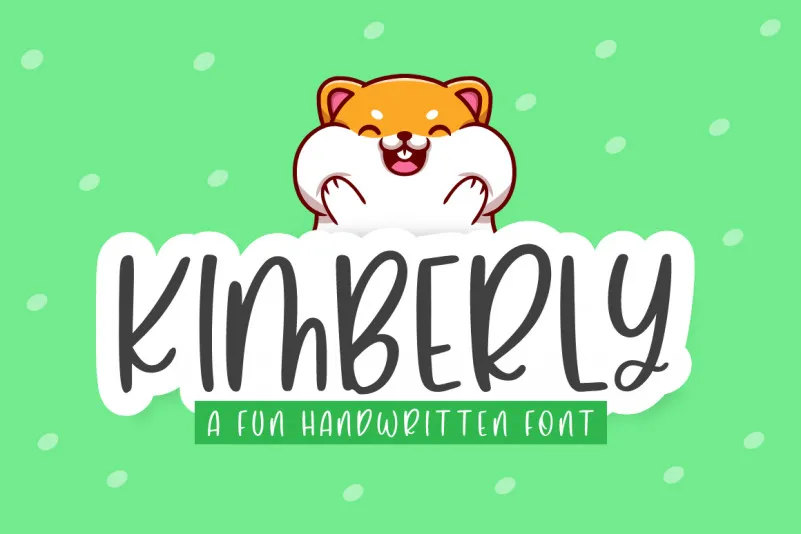
A Kimberly Font é uma alegre fonte escrita à mão que adora se tornar parte do seu design. A letra tem uma expansão na cabeça, e sua simplicidade faz com que seja perfeita para uma variedade de aplicações gráficas. Esta fonte é ideal para SVG design, criação handmade, cartões, camisetas, citações, design para notas, mugs e até mesmo design infantil. Ela oferece um toque único e divertido à suas criações digitais, tornando-a uma escolha ótima tanto para designers profissionais quanto para amadores que desejam um estilo personalizado em seus projetos. Não perca a oportunidade de dar vida aos seus designs com este encantador tipo à mão.